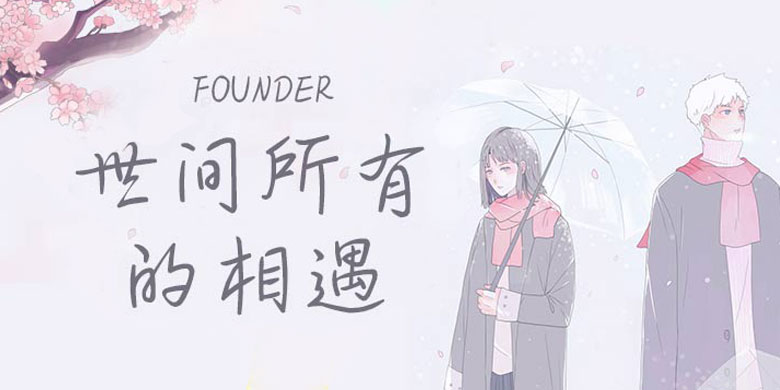
品牌:方正手迹设计师:余丹发行时间:2020字库编码:大陆简体(GB2312-80)分类:常规书写·硬笔字体属性:精品字
世间所有的相遇是一款书写流畅的行书风格字体。用笔圆润流畅,转折多柔软圆弧,整体视觉舒服。连笔较少给人一种干净简约的感觉。适用于文艺类书刊,及现代诗歌、短文的排版以及文化、商业类品牌的广告语设计。